该字体字体风格稳重呈方块形,整体特征坚硬、有力。具有现代、国际化的指向性;字形紧凑,但不失美感;刚正而不失稳重,横竖笔画加人了尖突的效果,让字形更显英朗气质;突出个性,端庄秀美。
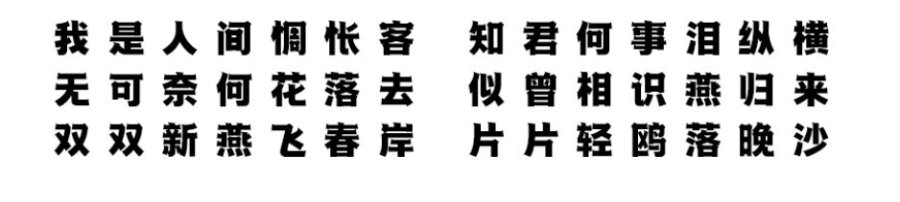
字体笔画采用较为接近宋体做法,但笔画整体更加大气,直线与曲线交汇,特点是横笔呈直角梯形,笔画整体粗细均匀,字体柔美稳重但又不失大气浑厚,整体给人一种稳重踏实的感觉。适用于标志、广告标语、商业广告、海报字体等。